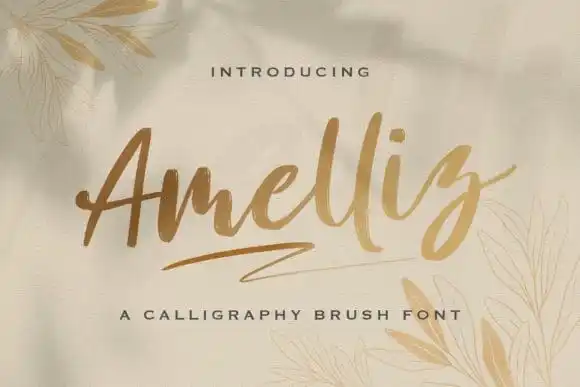
Amelliz Brush Font – Download Grátis
Amelliz Brush Font é uma elegante fonte script ideal para qualquer projeto que busque personalidade e sofisticação. Seu design delicado foi criado com a ajuda de um ponteiro de caneta elegante, resultando num estilo exuberantemente versátil. Perfeito para enfeitar letras finas em livros, quotes ou logotipos; destacar títulos e cabeçalhos; criar cartazes de estação criativos e até mesmo para elaborar uma invitacional de casamento incrível, postagem social chamativa ou arte digital cheia de vida. Essa fonte é perfeita tanto para designers como para aqueles que buscam uma maneira única de expressar seu estilo em projetos gráficos. Descubra a sua própria paleta de possibilidades com Amelliz Brush Font, da StringLabs.